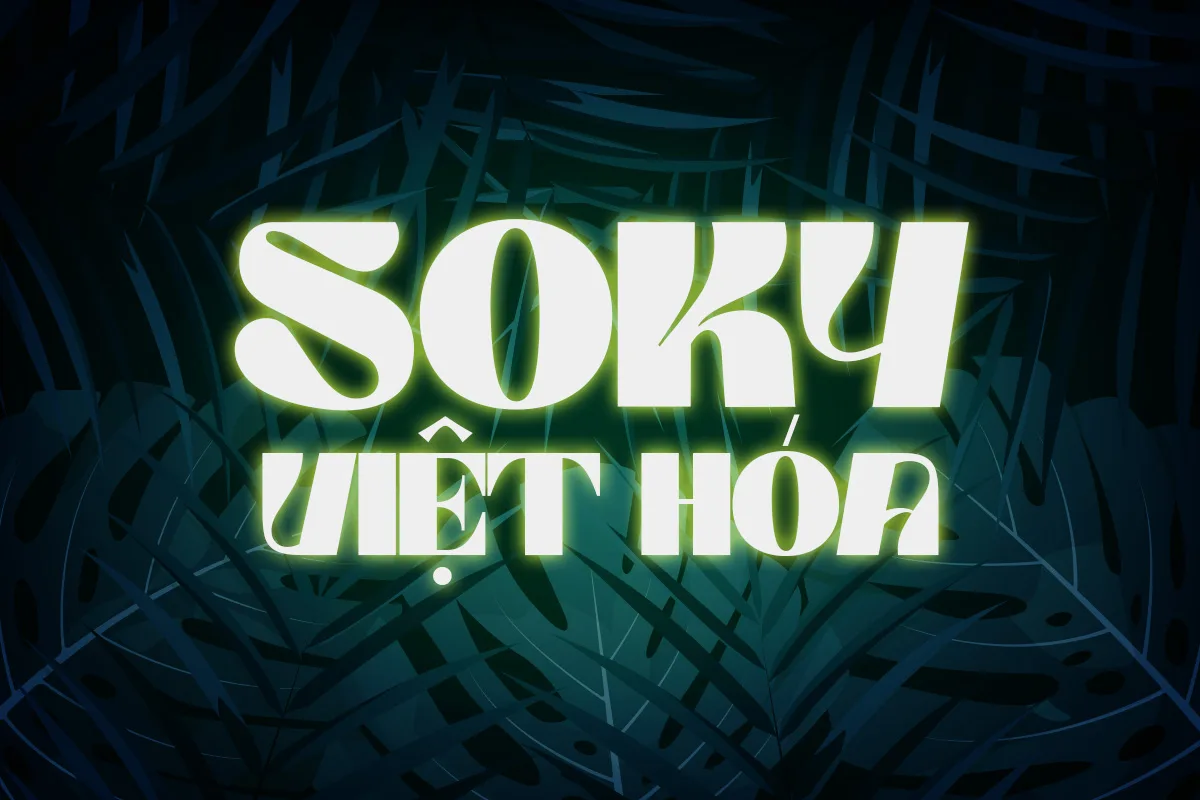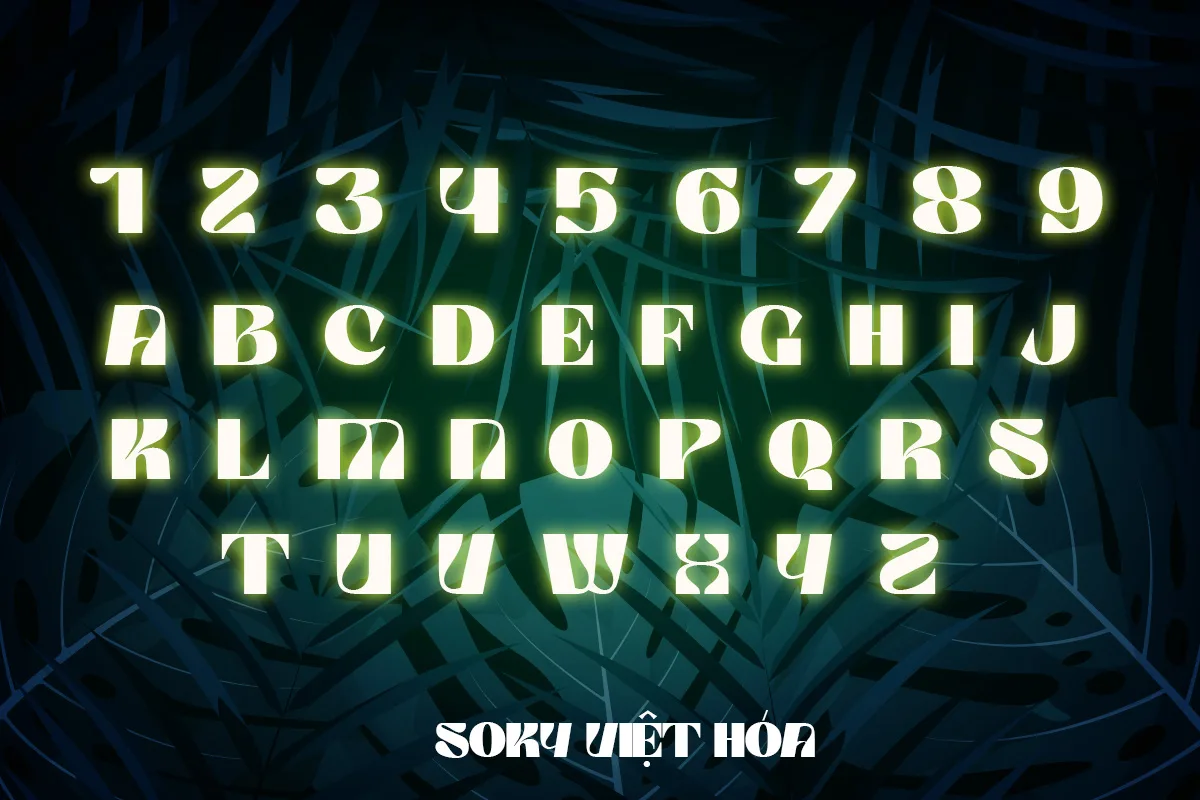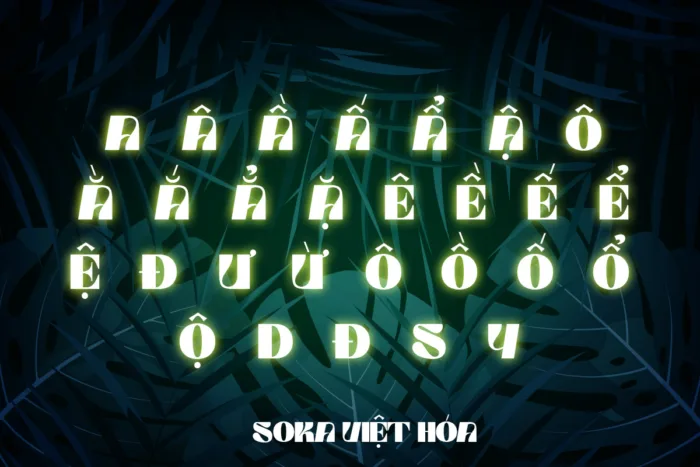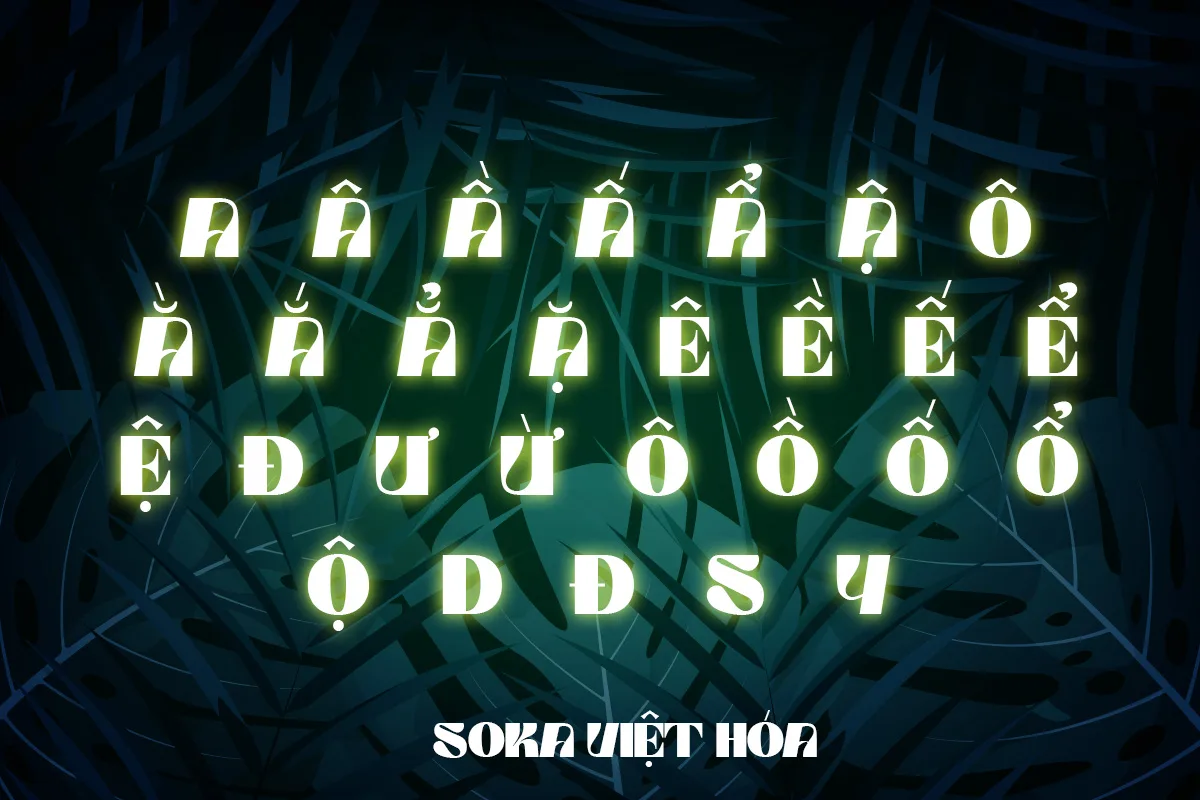
DVN SOKY Việt hóa – Font chữ hình khối hiện đại, đầy tính cắt xẻ táo bạo
SOKY Việt hóa là kiểu chữ display ấn tượng với thiết kế hình khối mạnh mẽ, nét cắt dứt khoát và tương phản cao. Font mang đến cảm giác hiện đại pha chút retro, phù hợp cho các thiết kế tiêu đề, poster, bìa sách, bìa nhạc hoặc các dự án nhận diện đòi hỏi yếu tố hình học độc đáo.
Các ký tự trong SOKY như được “tách đôi” bằng lưỡi dao sắc lạnh, gợi cảm giác điện ảnh, công nghệ hoặc sci-fi. Bộ font hỗ trợ đầy đủ tiếng Việt cùng nhiều ký tự đặc biệt và dấu câu, sẵn sàng cho mọi ứng dụng sáng tạo.
Nếu bạn đang tìm một font chữ vừa gây ấn tượng thị giác mạnh mẽ, vừa mang tính nghệ thuật cao, SOKY Việt hóa chính là lựa chọn đáng thử.